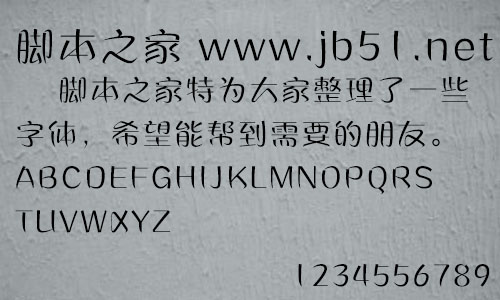
方正的達(dá)體簡(jiǎn)是由方正字庫(kù)出品的藝術(shù)字體,設(shè)計(jì)靈感源于《本草綱目》書(shū)中許多的奇花異草,其中有一款的形狀特別且可愛(ài)的“的達(dá)草”,適合應(yīng)用于藝術(shù)設(shè)計(jì)、平面宣傳設(shè)計(jì)、網(wǎng)頁(yè)設(shè)計(jì),書(shū)法字帖等領(lǐng)域。